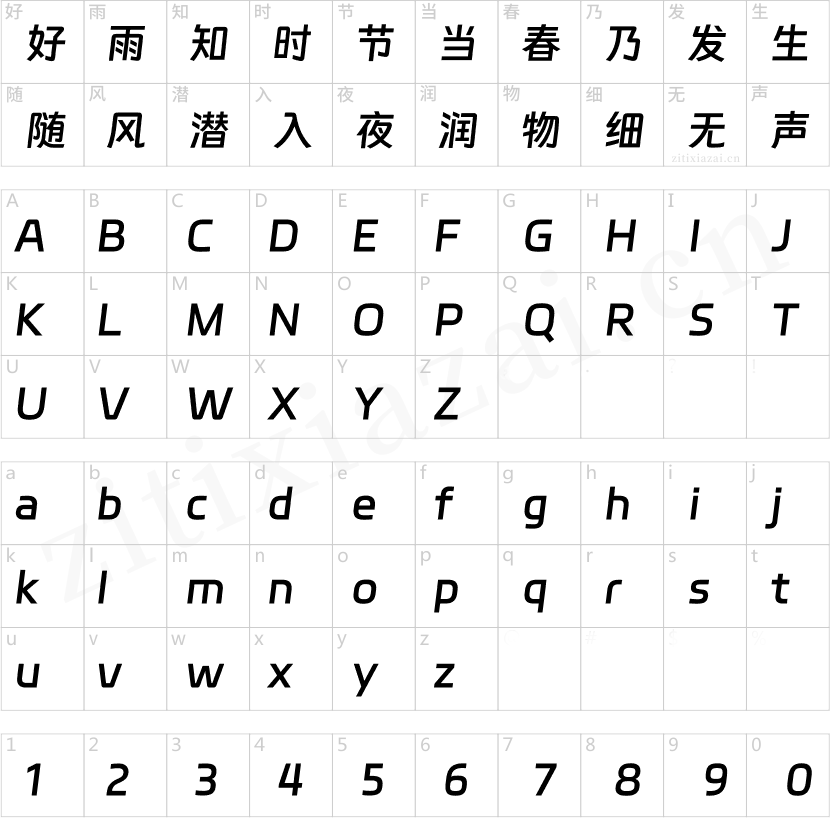
钉钉进步体
• 字体说明:钉钉以普惠开放的思路,联合国内一线字体团队打造一款原创的钉钉品牌字库--钉钉进步体。 钉钉进步体涵盖了中、英文7526个字符,字体专为标题、美术字等场景而生,科技活力的同时兼具自然书写美感,并开放给所有个人和组织--永久免费商用,帮助所有人和中小组织不必苦于字体版权购买和纠纷,用上更好更专业的设计,共同进步!
01.字体简介
钉钉以普惠开放的思路,联合国内一线字体团队,打造一款原创的钉钉品牌字库--钉钉进步体。
钉钉进步体涵盖了中、英文7526个字符;字体专为标题、美术字等场景而生,科技活力的同时兼具自然书写美感,并开放给所有个人和组织--永久免费商用,帮助所有人和中小组织不必苦于字体版权购买和纠纷,用上更好更专业的设计,共同进步!
02.字体特点
钉钉进步体字体以7°做倾斜,弯钩笔画的弧度向上,让整款字体年轻富有活力,使其在标题场景应用时,更具特点和美感。
结合最新钉钉品牌语言,我们在保持科技敏捷感的同时,希望字体可以更具人文温度,保持亲和不锐利,所以采用外圆内方的圆角处理方式,并对不同笔划的字体进行了简洁处理,既保正了笔划多的字能简洁不拥挤,又维持了笔划少的字体完整性,在既要优美感又要阅读感的情况下,做到了平衡。